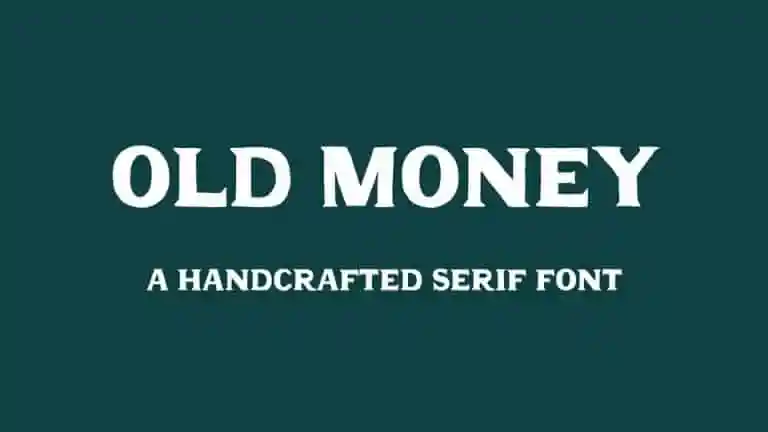
Old Money Display Font – Download Grátis
Introduzimos uma nova fonte chamada “Old Money Display Font”, um elegante tipo de serif vintage que captura os resquícios do passado. Desenvolvida pelo designer AZetype, esta fonte transmite um olhar nostálgico e rústico, ideal para criações gráficas que precisam de uma aparência memorável e sofisticada. Com seu design cuidadosamente elaborado à mão, “Old Money Display Font” oferece a oportunidade de recriar o glamour do passado, seja em selos de correio antigos ou no texto de um cartão de presente. Com sua elegância distinta e linhas arredondadas, esta fonte será uma escolha perfeita para qualquer projeto que deseja transmitir estilo e sofisticação em uma atmosfera vintage.